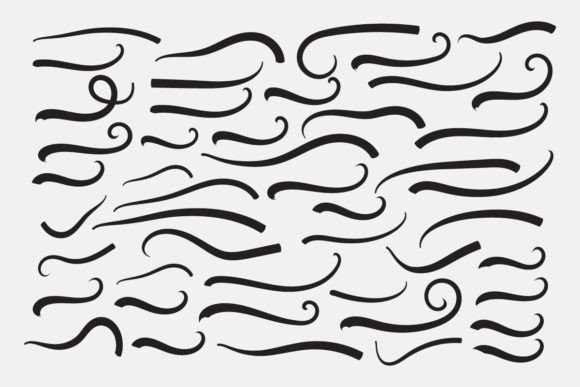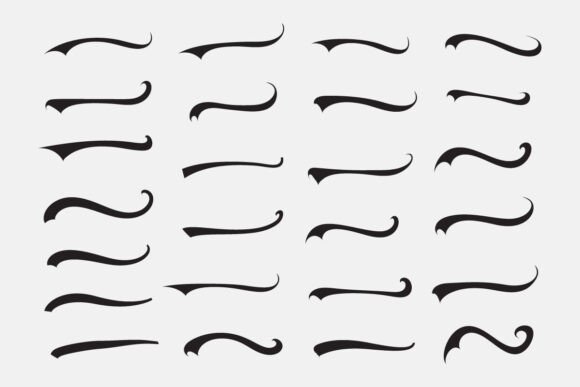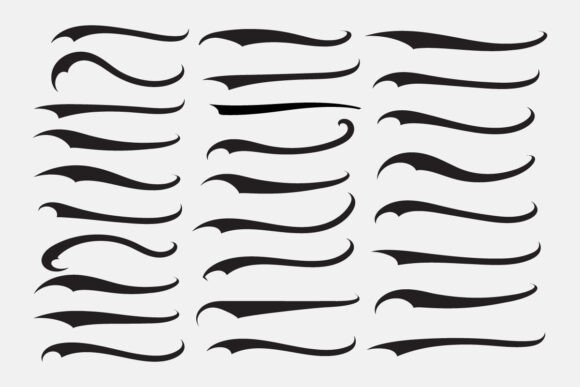
Font Swoosh Tails Ornamental Vector
หากคุณกำลังมองหาเนื้อหาคุณภาพสูงเช่น Font Swoosh Tails Ornamental Vector แพ็คเกจพรีเมียมนี้เป็นตัวเลือกที่ยอดเยี่ยมสำหรับโปรเจ็กต์สร้างสรรค์ของคุณ
สร้างขึ้นอย่างแม่นยำ Font Swoosh Tails Ornamental Vector ให้เวกเตอร์ที่สะอาด พิมพ์ตัวอักษรที่ราบรื่น และใบอนุญาตเชิงพาณิชย์เพื่อความสบายใจ
ไม่ว่าคุณจะสร้างผลิตภัณฑ์ POD (Print on Demand) คำเชิญงานแต่งงาน หรือกราฟิกโซเชียลมีเดีย Font Swoosh Tails Ornamental Vector ก็เหมาะสมอย่างยิ่ง